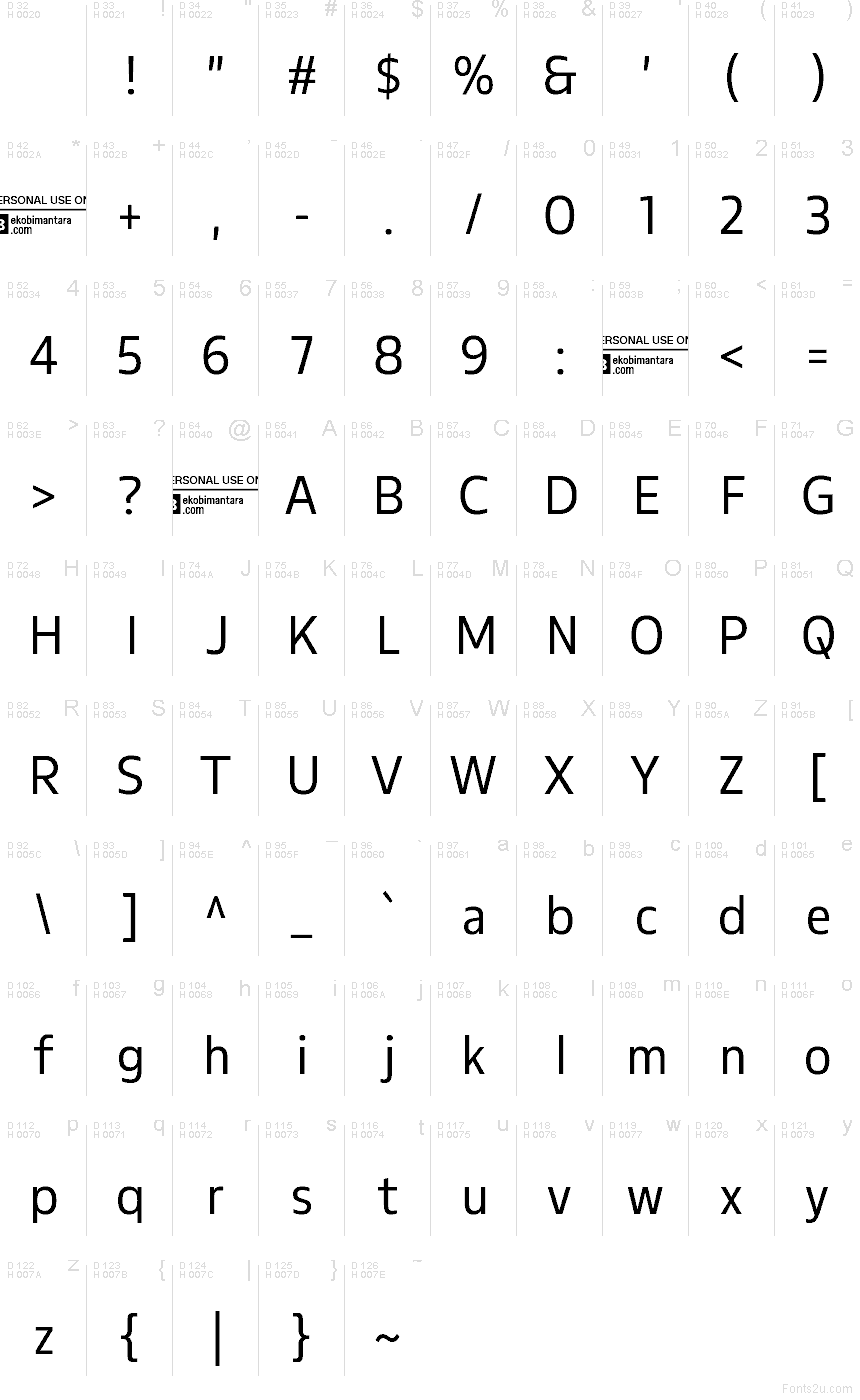
Profa Trial Condensed od Eko Bimantara je bezplatné úzke bezpätkové písmo s pokojným, súčasným charakterom. Písmená sú vysoké a aerodynamické, pričom mäkké zaoblené tvary dopĺňajú rovné, úsporné ťahy. Písmo tak pôsobí upravene, mestske a sebavedomo, no nie stroho.
Hodí sa na branding, titulky na plagátoch, časopisecké nadpisy, obaly a grafiku aplikácií, kde je málo miesta, ale štýl musí zostať aktuálny. Keďže ide o bezplatné písmo, je ideálne aj na úvodné obrazovky a krátke citáty, pretože vďaka úzkemu rytmu a čistým krivkám dodáva krátkym slovám kompaktný a vyvážený vzhľad.